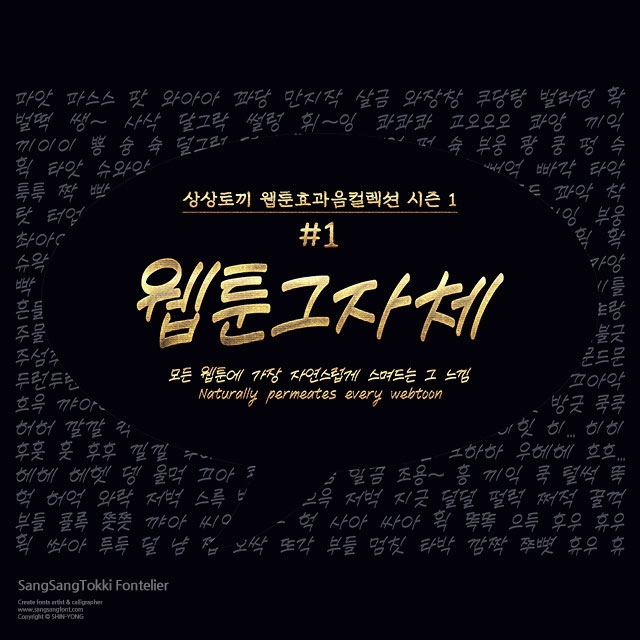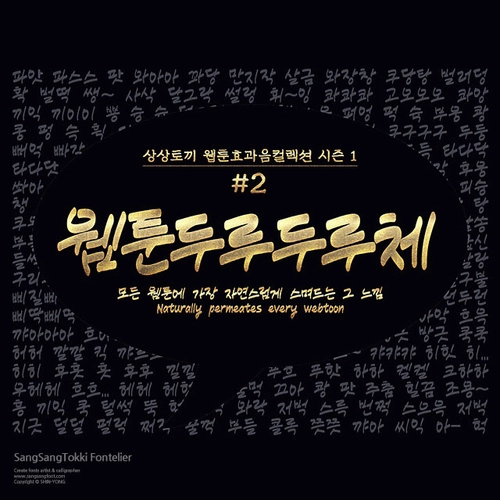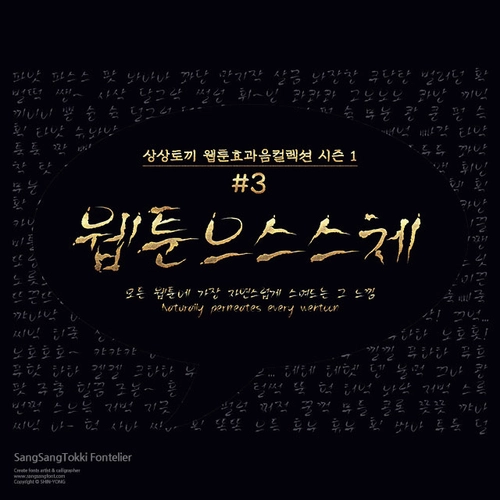
웹툰효과음컬렉션 시즌1, 4종
상상토끼의 웹툰 작가들을 위한 효과음 폰트 패키지 웹툰효과음컬렉션 시즌1, 4종
한글 11,172자 / 영문 52자 / 약물 84자
웹툰그자체 1종
웹툰두루두루체 1종
웹툰으스스체 1종
웹툰바람체 1종
| <웹툰효과음컬렉션>은 웹툰 작가들의 효과음 폰트 선택 고민을 조금이나마 덜어주기 위한 목적으로 기획되었습니다. 효과음 작업시에 상황에 맞는 개성있는 폰트들을 선택하여 사용할 수 있습니다. |
| <웹툰효과음컬렉션> 시즌1은 일반적인 웹툰 효과음으로 가장 잘 어울리는 웹툰그자체, 웹툰 효과음뿐만 아니라 여기저기 두루두루 잘 어울리는 웹툰두루두루체, 공포 스릴러물에 찰떡궁합인 웹툰으스스체 그리고 무협이나 스포츠물에 잘 어울리는 웹툰바람체까지 총 4종으로 구성되어 있습니다. |
| <웹툰효과음컬렉션>은 웹툰 효과음에 최적화한 폰트 프로젝트인 만큼 웹툰 작품에 삽입한 샘플컷 위주로 나머지 설명을 대신하겠습니다. 데모 폰트 테스트에 도움을 주신 장성준 작가님, 수리부 작가님, 강견/시바견 작가님, 윤성/라군 작가님, 혁씨 작가님, 이연 작가님, 가천가/은하수/주시하 작가님, 칸트웍스/구물 작가님, 봉이/갈피/오윤 작가님께 진심으로 감사드립니다. #1 웹툰그자체 가장 일반적인 스타일로 일상물이나 스포츠물의 효과음등 대부분의 웹툰에 전반적으로 잘 어울리는 웹툰그자체입니다. 부드러운 외곽선을 사용했지만, 임팩트 있는 장면에도 위화감 없이 잘 어울리기 때문에 잔잔한 일상물에서부터 스피디한 액션물까지 무난하게 사용 가능합니다.
▲ 가천가/은하수/주시하 작가님의 「북부 공작님을 유혹하겠습니다」 #2 웹툰두루두루체 여기저기 어떤 작업이든 두루두루 잘 어울리는 웹툰두루두루체입니다. 웹툰그자체보다는 좀 더 두꺼운 획을 가지고 있으며, 꼭 웹툰 효과음이 아니라 일반적인 문장으로 사용하는데도 불편함이 없습니다.
▲ 이연 작가님의 「살아남은 로맨스」 #3 웹툰으스스체 공포물이나 긴장되는 상황 연출에 적합한 웹툰으스스체입니다. 음산하거나 공포스러운 분위기가 필요할때 선택한다면 더할나위 없이 잘 어울리는 폰트입니다.
▲ 상상토끼의 「드로잉북 中」 #4 웹툰바람체 활동적이거나 임팩트 있는 효과음에 잘 어울리는 웹툰바람체입니다. 날카롭고 속도감이 있는 획을 사용하여 액션이나 무협등 스피디한 분위기 연출에 더욱 잘 어울립니다.
| <웹툰효과음컬렉션>은 한글 11,172자 / 영문 56자 / 약물 84자를 지원하기 때문에 짧은 단어로 이루어진 웹툰 효과음 뿐만 아니라 일반적인 문장에서도 사용 가능합니다. |
| 또한 조합할 수 있는 모든 경우의 한글을 지원하기 때문에 "똠양꿍"이나 "펲시콜라"와 같은 외래어는 물론 "쀐썀뽉딽" 같이 맞춤법에 어긋난 외계어까지도 표기 가능합니다. |